Dropbox annuncia il suo rebranding e introduce un po' di colore all'estetica bianca e blu precedente. L’identità del servizio di archiviazione è ora più espressiva, dinamica e giocosa.
Il nuovo look comprende un logo flat: la scatola (super sottile) è aperta, proprio come la vision di Dropbox che rappresenta una piattaforma, un 'luogo aperto' per la creazione e la circolazione di idee.
L’estetica appare rinnovata grazie a uno schema che sovrappone coppie di colori in modo audace e inaspettato.
Il nuovo design cambia faccia a seconda della situazione e rappresenta il primo grande passo verso una fase di rinnovamento della società che ben si sintetizza nella frase “The world needs your creative Energy”.
Il rebranding si ispira al lavoro creativo delle persone: “Non è necessario essere un pittore o un documentarista. Vogliamo tutti fare un lavoro che abbia un significato, che rifletta le nostre idee e il nostro potenziale” si legge sul blog ufficiale.
A 10 anni dalla nascita, Dropbox intende rafforzare la sua immagine e differenziarsi dai suoi più grandi competitor come Microsoft One Drive e iCloud, che incorporano una versione blu nei loro loghi.
Il nuovo font Sharp Grotesk e le tante combinazioni colore rendono l’immagine minimal e all'avanguardia per favorirne il riconoscimento sul mercato.
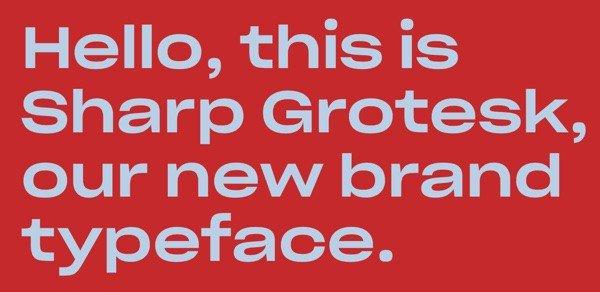
“Siamo determinati nell'apportare un cambiamento positivo e significativo nella cultura del lavoro moderno. Vogliamo scatenare l'energia creativa del mondo” ha scritto Carolyn Feinstein, Chief Marketing Officer di Dropbox.
Al momento i cambiamenti non sembrano interessare l’interfaccia del sito ad esclusione del logo. A partire dalle prossime settimane la nuova filosofia di Dropbox coinvolgerà tutti i prodotti.
Il servizio di file sharing ha annunciato il lancio di una vera e propria campagna pubblicitaria globale che partirà dagli Stati Uniti e arriverà fino in Australia: “in città e quartieri dove le persone creative vivono e lavorano".